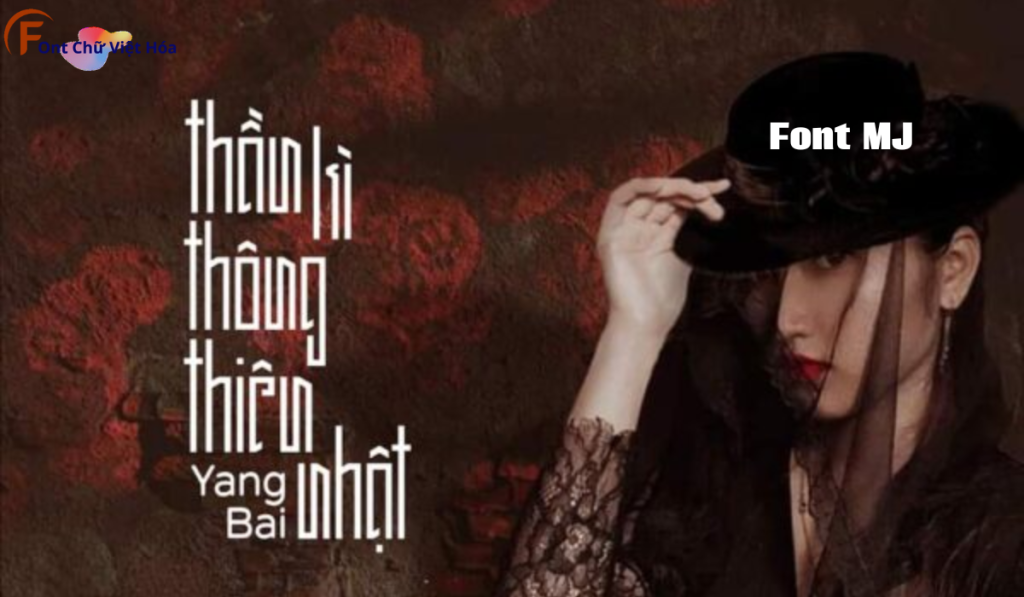
Font MJ Ohex Việt Hóa
Tác giả: MJ Ohex
Ngày phát hành: 7/2024
Bộ Font: MJ
Độ dày: Thường, đậm
Font MJ Ohex Việt Hóa là một font chữ không chân cá tính, thuộc bộ font MJ. Được thiết kế với mục tiêu mang lại sự hiện đại và tinh tế, font này phù hợp cho các dự án thiết kế như poster, banner, và website. Với các nét chữ rõ ràng và độ dày đều đặn, Font MJ Ohex Việt Hóa không chỉ dễ đọc mà còn tạo cảm giác chuyên nghiệp. Việc Việt hóa font giúp người dùng dễ dàng sử dụng trong các thiết kế tiếng Việt, mang lại sự tiện lợi và thẩm mỹ cao.